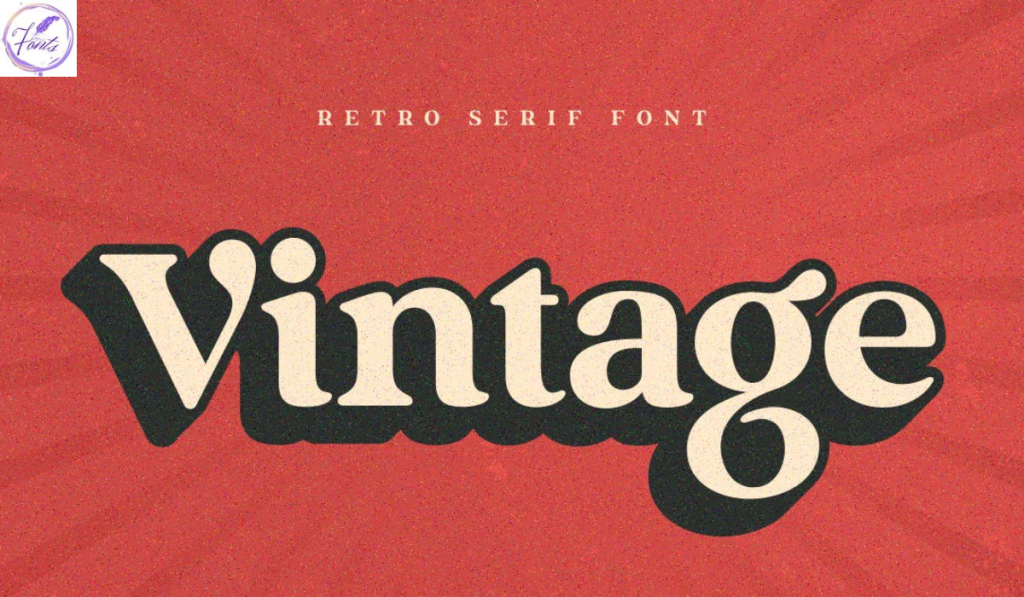
SVN Vintage One Font Việt hóa
Phân loại: cá tính, độc đáo
Kiểu chữ: serif
SVN Vintage One Font là một font chữ thuộc bộ font SVN mang đậm phong cách cổ điển, được thiết kế bởi Zamroni Hamzah vào năm 2016. Với những đường nét tinh tế và uyển chuyển, font chữ này mang lại cảm giác hoài cổ và sang trọng, phù hợp cho các dự án thiết kế cần sự độc đáo và ấn tượng. SVN Vintage One Font không chỉ hỗ trợ đầy đủ các ký tự chữ cái mà còn tích hợp các ký tự đặc biệt, giúp người dùng dễ dàng sáng tạo trong các ấn phẩm của mình.
Đánh giá svn vintage one font
SVN Vintage One Font đã nhận được nhiều lời khen ngợi từ cộng đồng thiết kế vì sự độc đáo và dễ sử dụng. Các nhà thiết kế đánh giá cao khả năng của font chữ này trong việc tạo ra các ấn phẩm mang đậm chất cổ điển nhưng vẫn giữ được tính hiện đại. Đặc biệt, phiên bản Việt hóa của SVN Vintage One Font giúp người dùng Việt Nam dễ dàng ứng dụng vào các dự án mà không gặp phải bất kỳ khó khăn nào. Font chữ này là sự lựa chọn hoàn hảo cho những ai muốn tạo ra các thiết kế tinh tế và đầy phong cách.